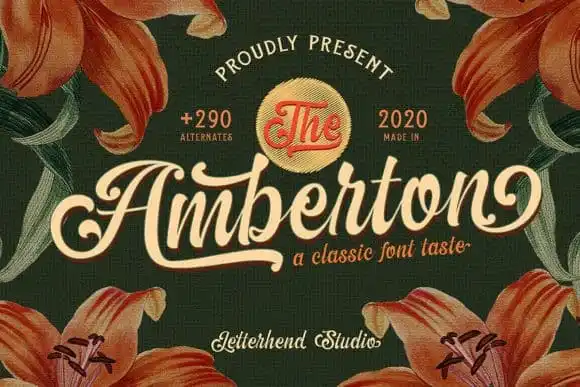
The Amberton Script Font
A fonte ‘The Amberton Script Font’ é uma opção elegante para aqueles que buscam algo único e autêntico no seu design. Esta fonte tem um estilo script robusto, com elementos inspirados nos ornamentos florais clássicos, criando um toque vintage e autêntico. O designer de 99designs fez deste font um elemento diferenciado com sua própria aposta em alternativas únicas, permitindo uma imensa flexibilidade ao criar gráficos ou mensagens personalizadas. Em cada caractere está presente cerca de 290 alternativas que permitem experimentar e desvendar novas formas de criação de texto. A fonte é perfeita para aqueles que buscam um touch distintivo em seus projetos digitais, tornando-a uma escolha inteligente para designer gráficos ou qualquer pessoa que adora incorporar personalidade no seu trabalho.